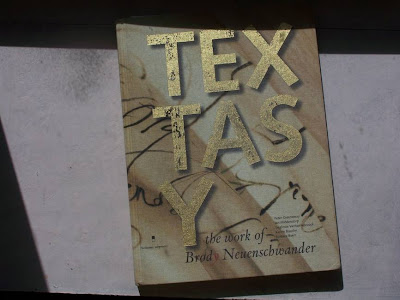
Art Postal : MAAV 2011, essais
Je fais des essais : Parallel Pen 6.0 mm rempli d'aquarelle "Charcoal grey" de W&N, plume Speedball C4 et encre de correction japonaise. Le premier essai est réalisé sur mon carnet "Fonds de matière et essai" (Hanhnemühle) et le second sur une chute d'Arches satin.
Manuscriptum est un des destinataires de Mail Art Across the World 2011.
Alphabet : chancelière redressée, décollée, redessinée 1.
Entraînement/recherches d'écritures : voici un alphabet réalisé au Parallel Pen 6.0 mm, rempli de brou de noix.
Réalisé au Parallel pen 6.0 mm, rempli avec de l'extrait de cassel. Le tracé reprend la structure d'une chancelière redressée de manière libre, l'outil décolle plus ou moins sur les tracés gras, les déliés sont réalisés avec le coin de l'outil. Souvent, une partie de la lettre est dessinée.
Un projet d'Art Postal d'envergure : Mail Art Across the World 2011
Après les éditions 2005, 2009, 2007 de Mail Art Across the World, MAAW 2011 est lancée. Voici ce qu'en disent les organisateurs :
A mi-chemin entre l'écriture, le dessin ou la peinture, entre le signifiant et le signifié, la calligraphie est un art hérité de notre histoire, de plus en plus présent autour de nous à travers la diversité de nos moyens de communication actuels : typographies, signes, traces...
Avec l’art postal, les échanges épistolaires retrouvent une vie nouvelle et se libèrent de leur fonction première pour voyager et offrir à leur destinataire leur œuvre de création et d’expression.
C'est au sein du 1er forum francophone de calligraphies (http://encre-et-lumiere.com) et de la rencontre de calligraphes de nationalités différentes qu'est né en 2005 le projet "Mail Art across the World". Il est depuis réédité tous les 2 ans.
Dans cet espace d'échanges et de ressources pour toutes les écritures, nous vous proposons de lancer un pont entre les passionnés de calligraphie du monde entier pour faire redécouvrir à tous cet incroyable art qu'est la calligraphie.
Cette année, quatre pays participent : la Belgique, la Hongrie, l'Ukraine et la France.
Bien sûr, je vais y participer, et en attendant j'en profite pour m'entraîner.
Exposition à l'Atelier Warjan : dernière semaine.
Bibliothèque calligraphique : TEXTASY....
En cette période de Noël, et donc de futurs (proches) cadeaux, je vous propose un petit tour dans ma bibliothèque calligraphique. L'ouvrage que je vous propose cette-fois-ci a été conçu par Brody Neuenschwander. Il nous présente un aperçu de son travail, sa conception de l'écrit plutôt que de la calligraphie seule. Il nous questionne d'ailleurs indirectement sur nos conceptions de la beauté de la lettre, et si vous ne connaissez pas les œuvres de cet artiste, attendez-vous à être surpris(e)s, bousculé(e)s. Est-ce ou non de la calligraphie ? Ce n'est pas la question. Est-ce que ces oeuvres vous interpellent, vous interrogent, vous apprennent, modifient vos convictions esthétiques ? Pour moi, la réponse est oui, vraiment.
De plus, le livre en lui-même, tout en restant d'un prix abordable, est le résultat de choix éditoriaux : plusieurs qualités de papier, un titre en lettres dorées et imprimées en creux, une mise en page qui fait une large place au blanc, des pages de garde surprenantes...
Exposition en cours à l'Atelier Warjan.
En ce moment j'expose une série de tableaux, une sélection de mes travaux des trois dernières années mais aussi des volumes et autres supports, en voici un aperçu ci-dessus.
L'exposition est visible jusqu'au 24 décembre, à l'Atelier Warjan à Saint-Renan.
Denis Brown : Snow calligraphy.
Voici la dernière vidéo calligraphique (dans un sens étendu) de Denis Brown.
La neige devient une page blanche.... et en accueillant l'encre, un objet de recherche visuelle.
Au programme du week-end dernier : dorure à l'or fin (en feuille ou à la coquille, peinture a tempera (pigments liés à l'œuf) sur parchemin, deux jours de silence studieux à caresser de la peau avec un pinceau en poil de martre.
J'ai choisi un modèle de bordure dans le "Bestiaire" de la BNF, vous voyez ci-dessous mon travail en cours et le modèle original.
Et puis voici une photo d'un bel oiseau placé dans une lettre art-déco, réalisé par une des stagiaires, Michèle V.